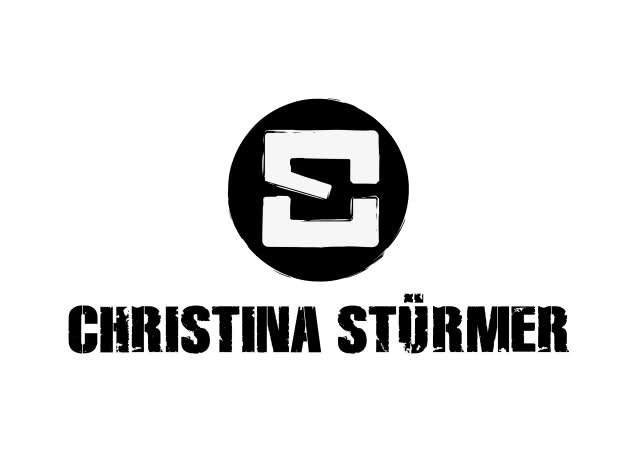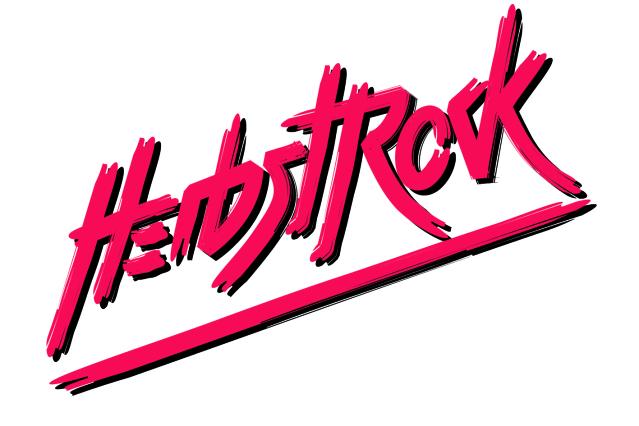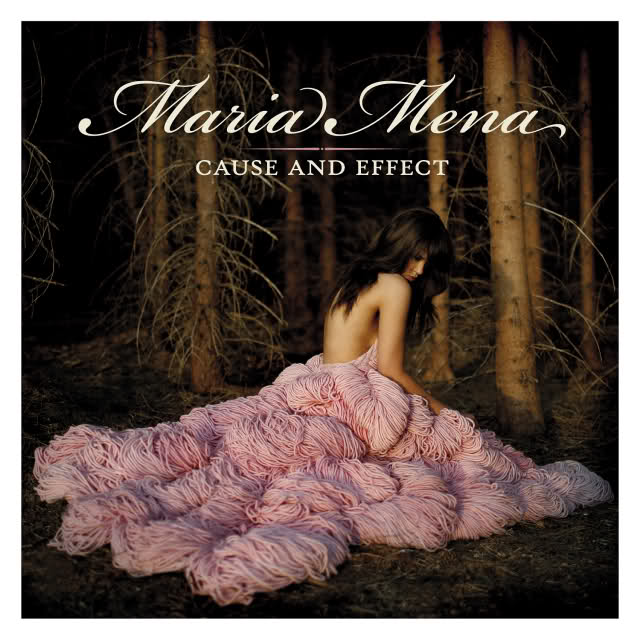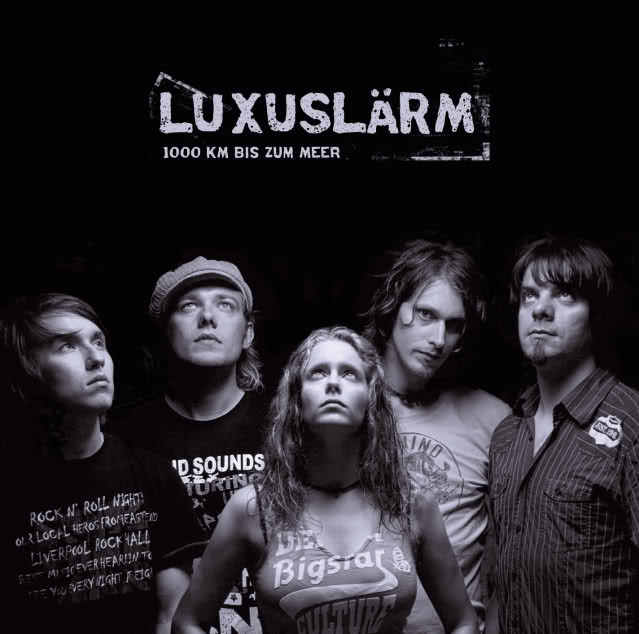
Suche dringend 3 (4) Schriften
Ich suche vergebens vier Schriften wobei ich glaube das eine davon ein Logo ist.
Einmal das neue Logo der Künsterlin "CHRISTINA STÜRMER". So sieht es aus:
Dann das der Band "LUXUSLÄRM".
So schauts aus: (Auch das 1000 Km bis zum Meer Logo ist ja das selbe wies ausschaut)
"MARIA MENA" hat auch ein Logo glaub ich aber es schaut auf der anderen Seite doch aus wie eine Font
Und das von "HERBSTROCK" wobei ich mir fast sicher bin dass es dann doch eher ein richtiges Logo ist, oder?
Solche Grunge-Fonts wie bei Christina Stürmer, die von der Impact/Helvetica Inserat/Schmalfetten Univers abgeleitet sind gibt es viele Dutzend. Um nur einige zu nennen: 84 Rock !, Impacted, Disintegration, Thirsty for Souls, CM Corruged, Viva Allende. Eleganter wäre natürlich ausdrucken, selbst derckig machen und einscannen.
Eleganter wäre natürlich ausdrucken, selbst derckig machen und einscannen.
"LUXUSLÄRM" dürfte so entstanden sein: die beiden U und L sind völlig unterschiedlich verdreckt. Schwer vorstellbar, dass man in diesem Bereich einen OT-Font mit etlichen Alternativzeichen für jeden Buchstaben produziert. Ja und "Herbstrock" ist ziemlich gewiss nicht in einem Font gesetzt.
Also neben Maria Mena Font (Kostenflichtig) hab ich nun auch die von Christina dank hey gefunden. Es gibt enorme Ähnlichkeit mit Disintegration, nur das eben leichte Veränderungen unternommen wurden.
Naja das Herbstrock ein Logo ohne Font ist, war klar.
Fehlt also nur noch Luxuslärm aber ich glaube Steff11 hat recht, muss aber dazu sagen dass ich von Fonts eher wenig Ahnung habe, also in jedem Fall DANKE AN ALLE!!